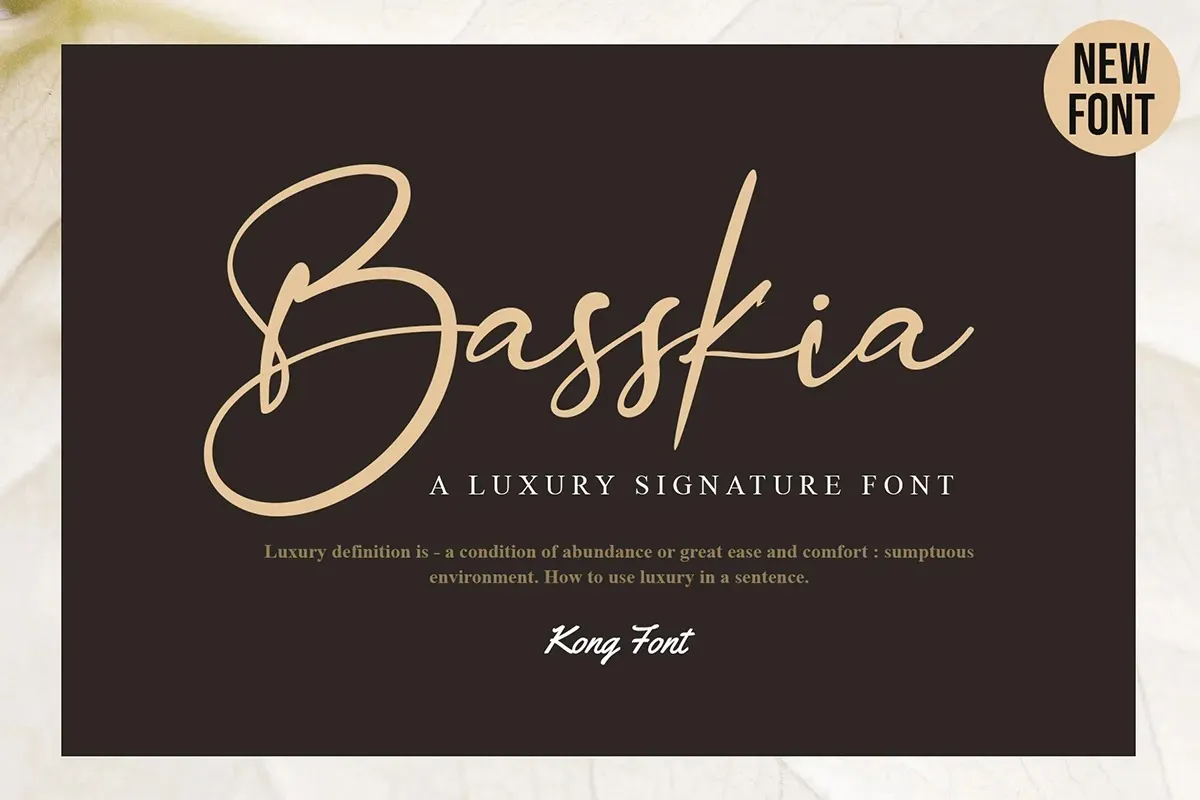
Basskia Font – Download Grátis
A Basskia Font é uma elegante tipografia script que surpreende por sua disposição graciosa e seu charme inegável. Suas letras dançam harmoniosamente sobre a linha de base, criando um visual encantador e vibrante. Perfeita para ideias mais criativas, essa fonte eleva qualquer projeto e faz o trabalho destacar-se. Ideal tanto para uso em editoriais como em logotipos, casamentos e até mesmo cabeçalhos, a Basskia Font se torna uma escolha perfeita para quem busca dar um toque único às suas criações. Não importa qual seja seu projeto ou estilo, a Basskia oferece o suporte necessário para transformá-lo em algo mais memorável e impactante. Esta fonte é como uma convidativa mão de criatividade que promete fazer seus projetos se destacarem ainda mais. Com sua facilidade em manusear e grande variedade de aplicações, a Basskia Font está destinada a ajudá-lo a alcançar seu máximo potencial, tornando cada projeto um verdadeiro trabalho de arte.